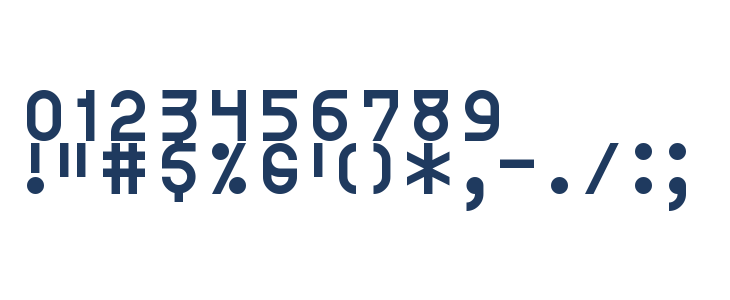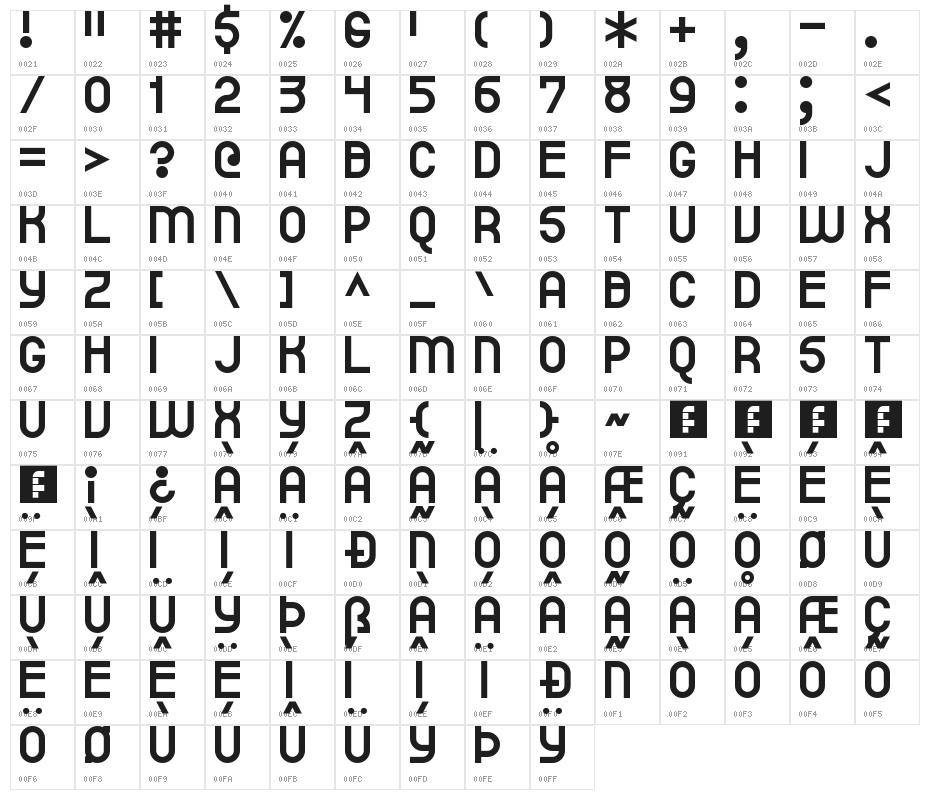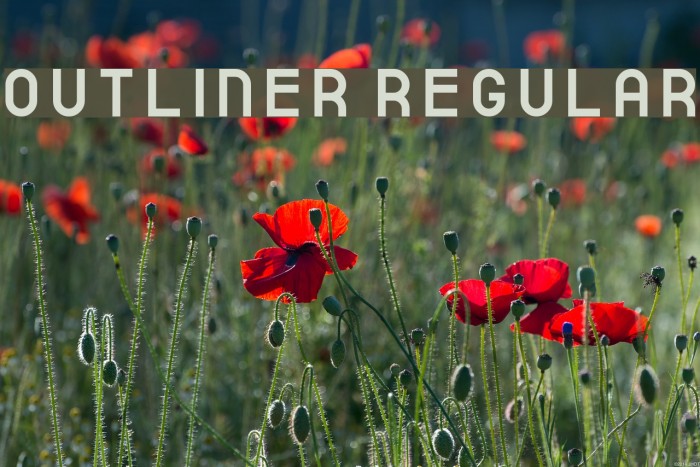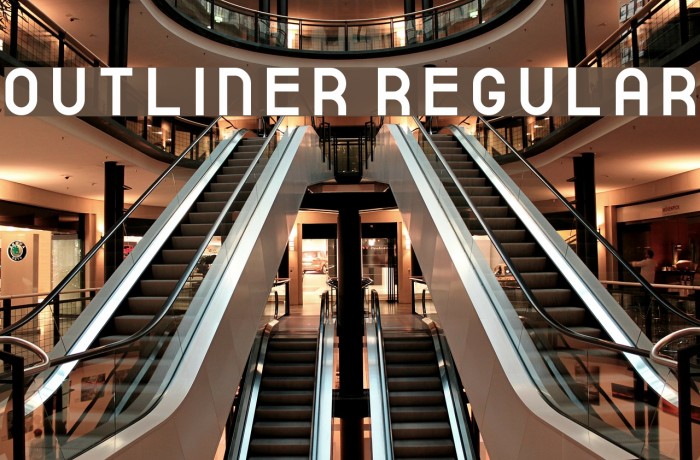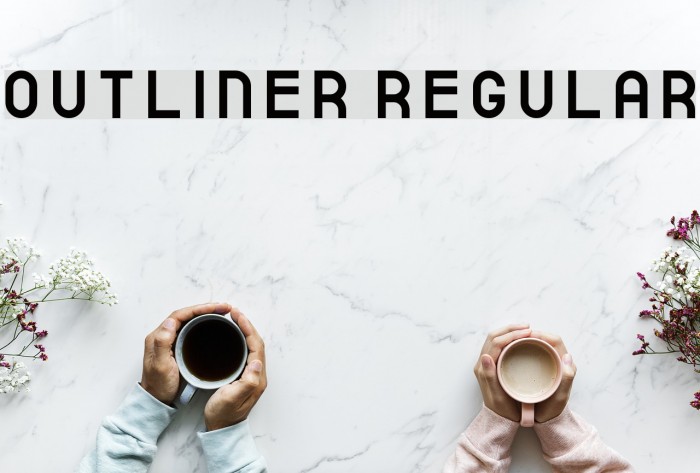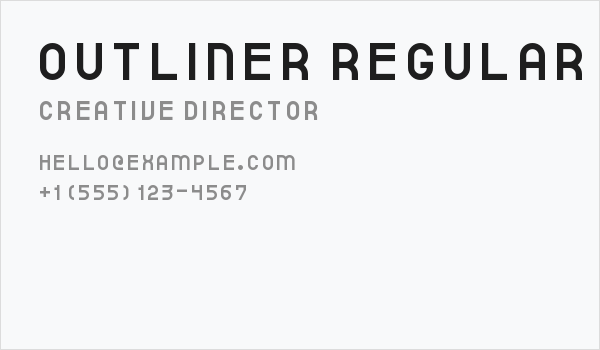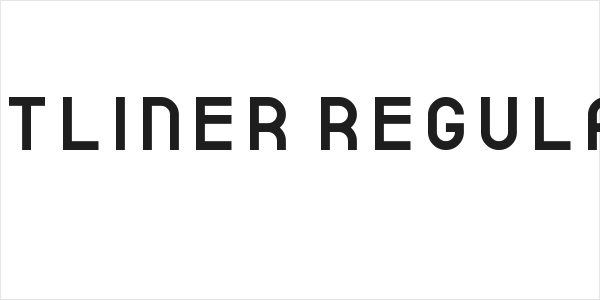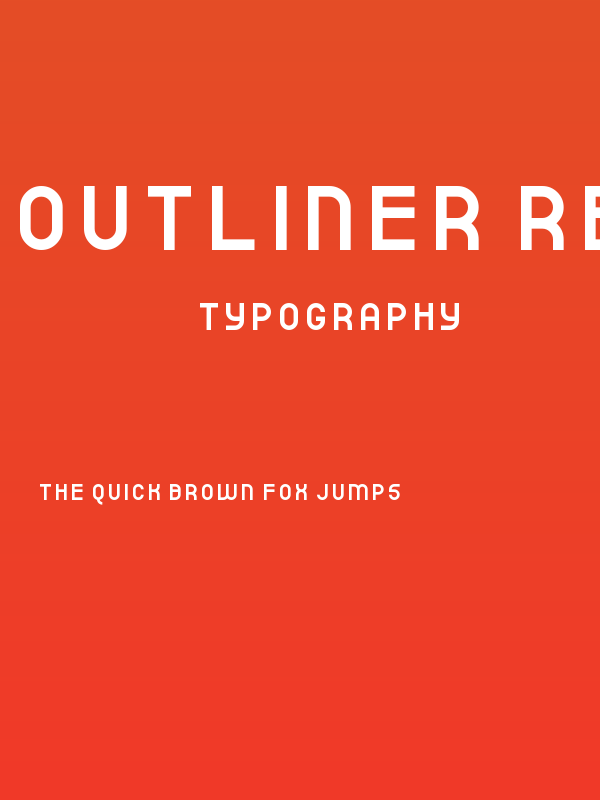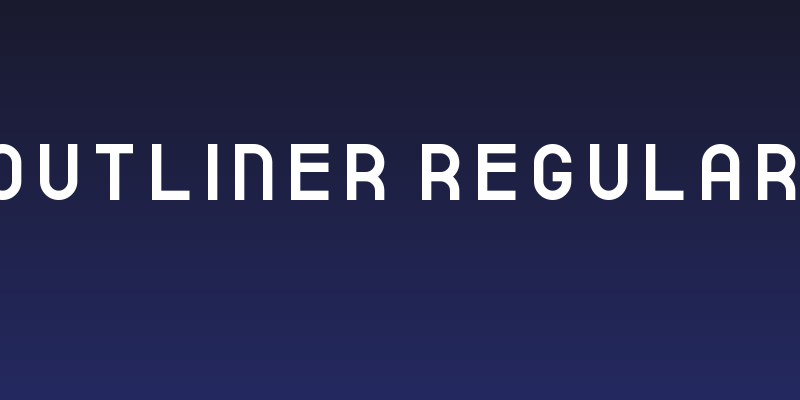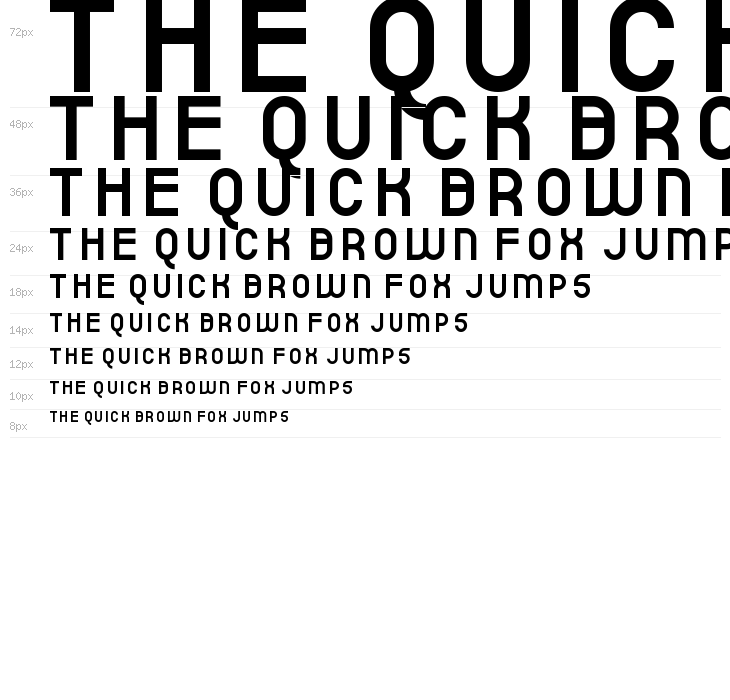
outliner Regular Font
| Vorgeschlagene Projekte | Ideal for branding, headlines, posters, and digital interfaces where a modern and bold statement is needed. |